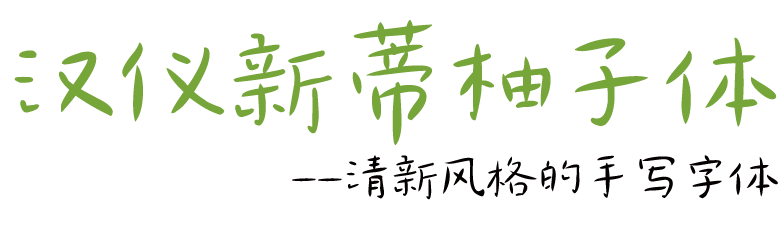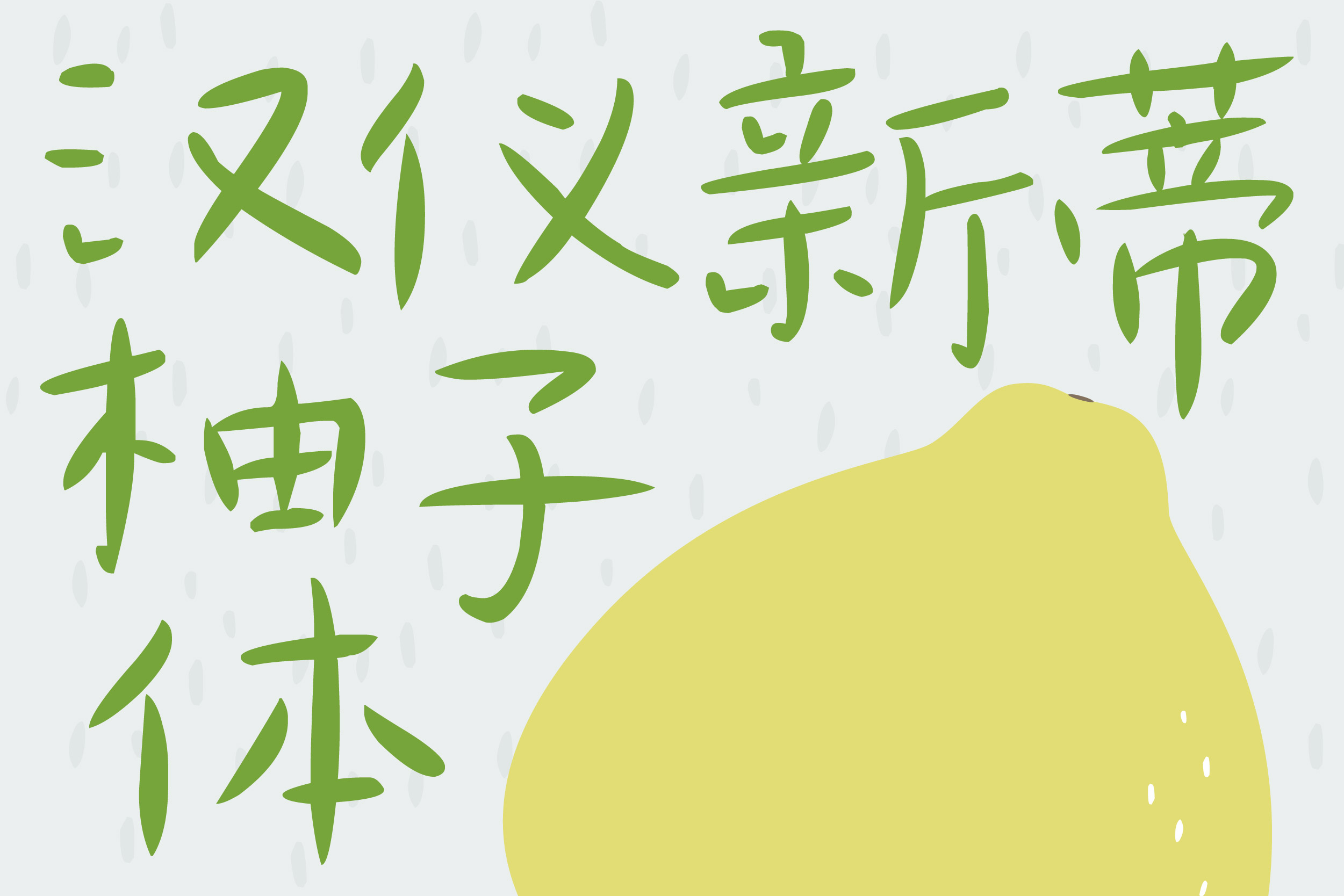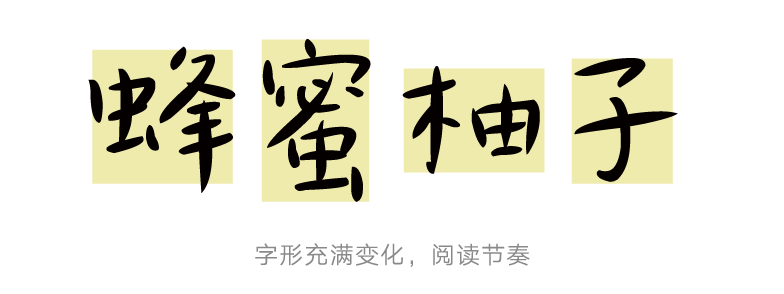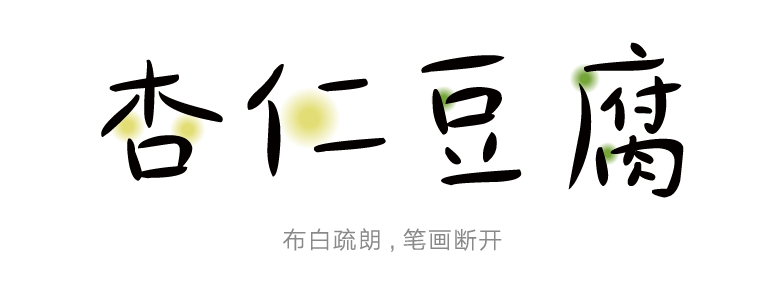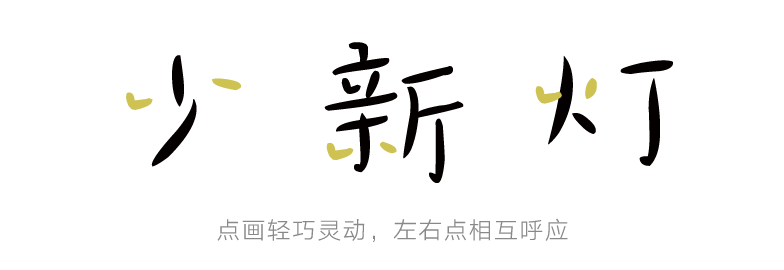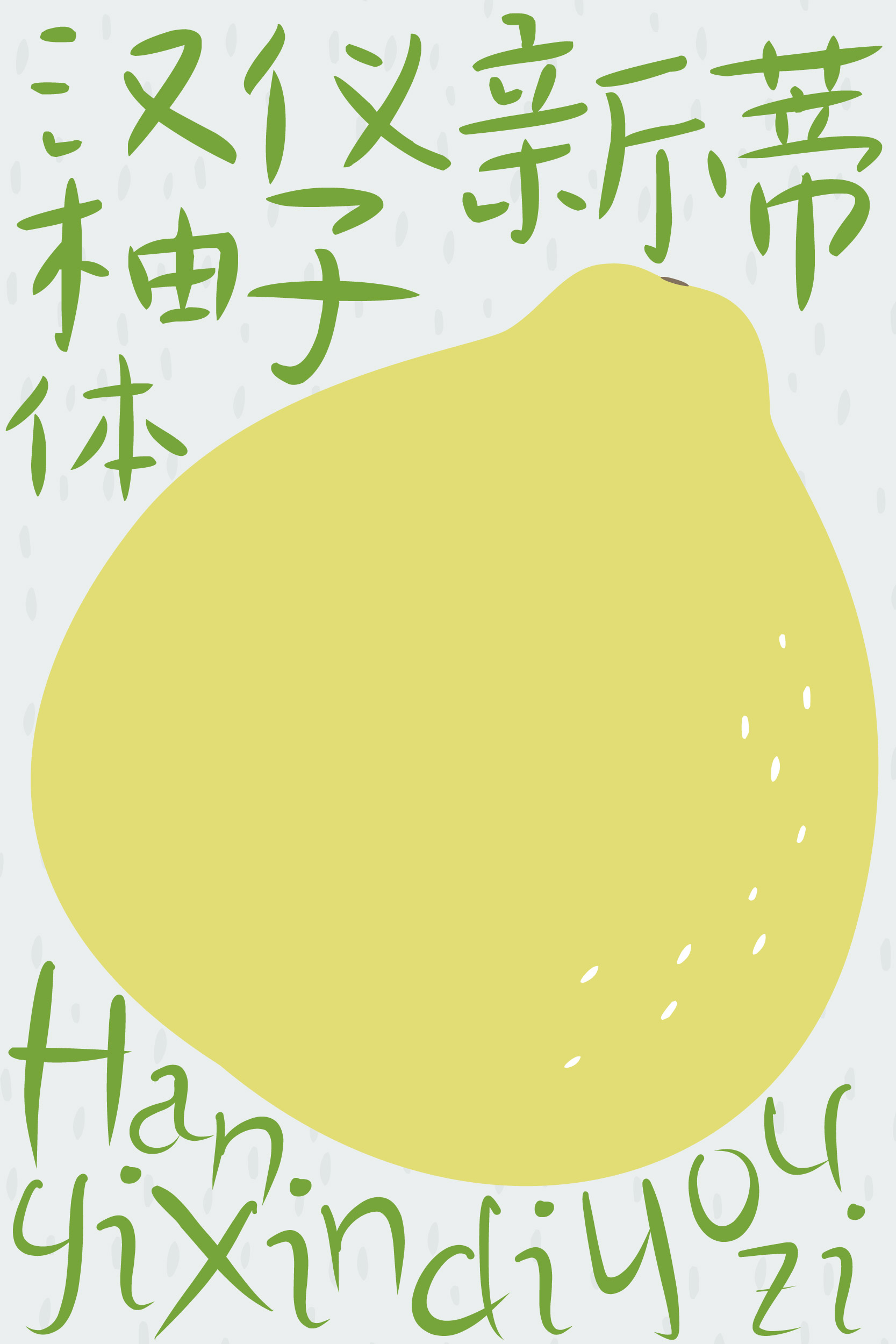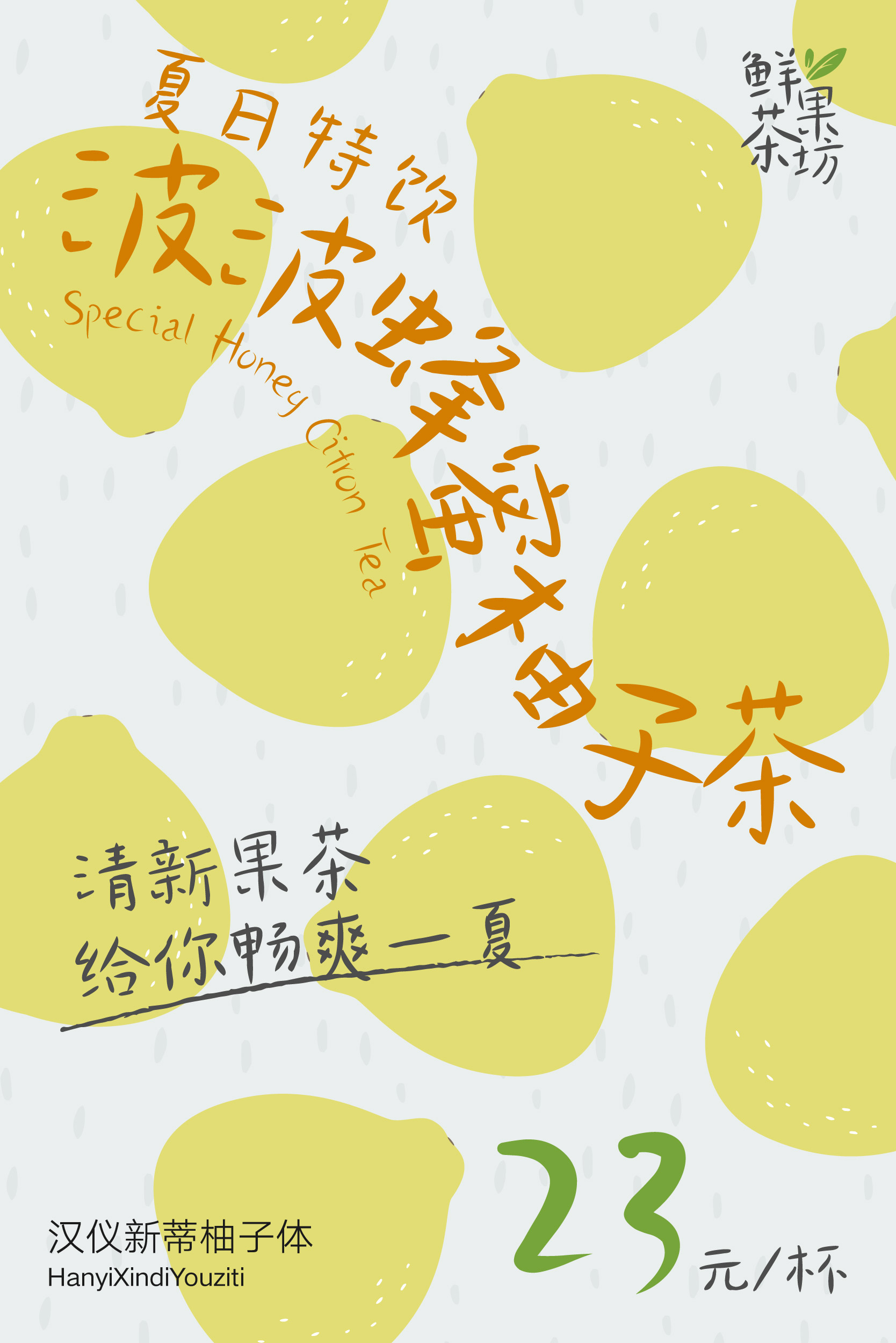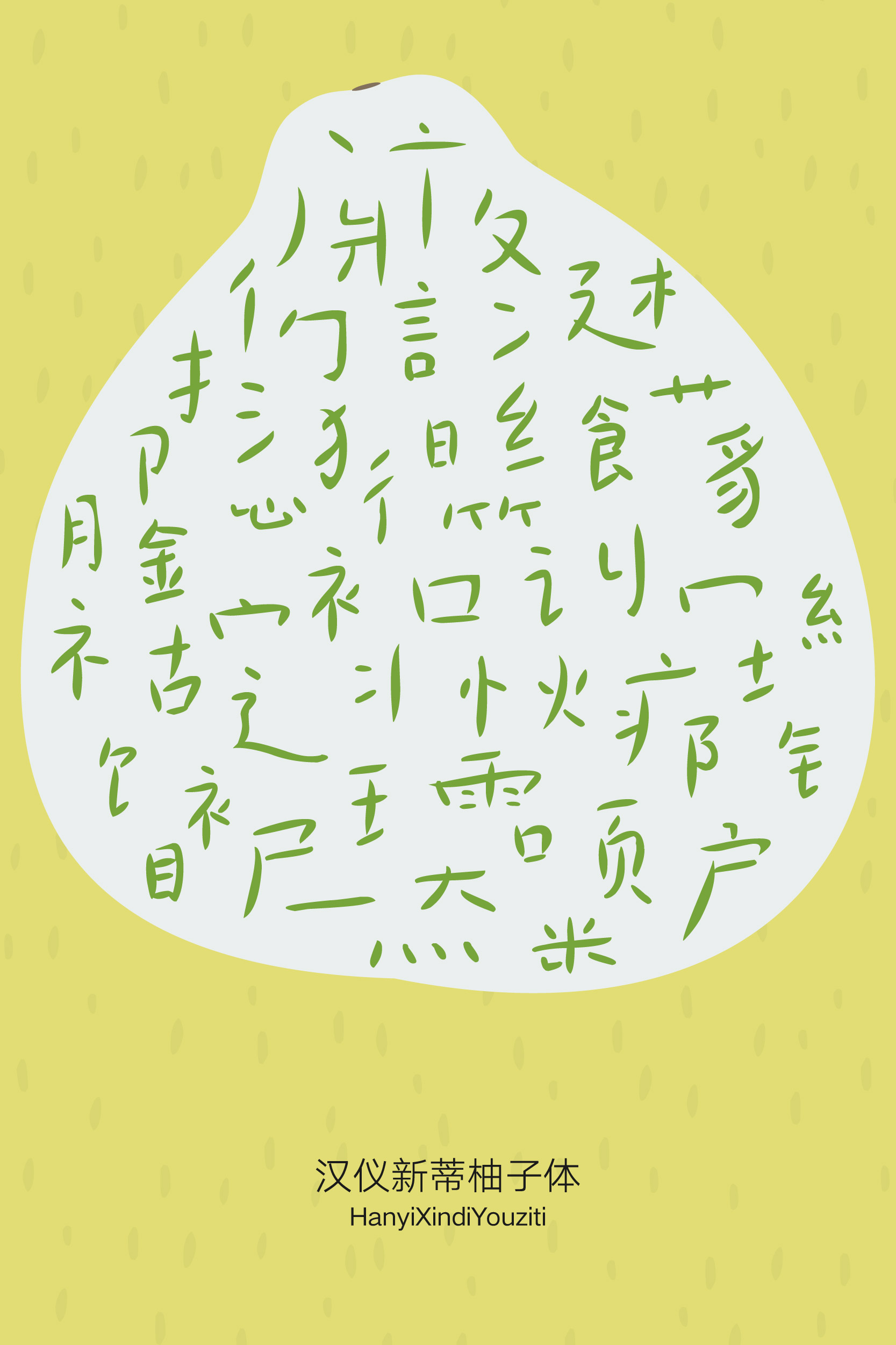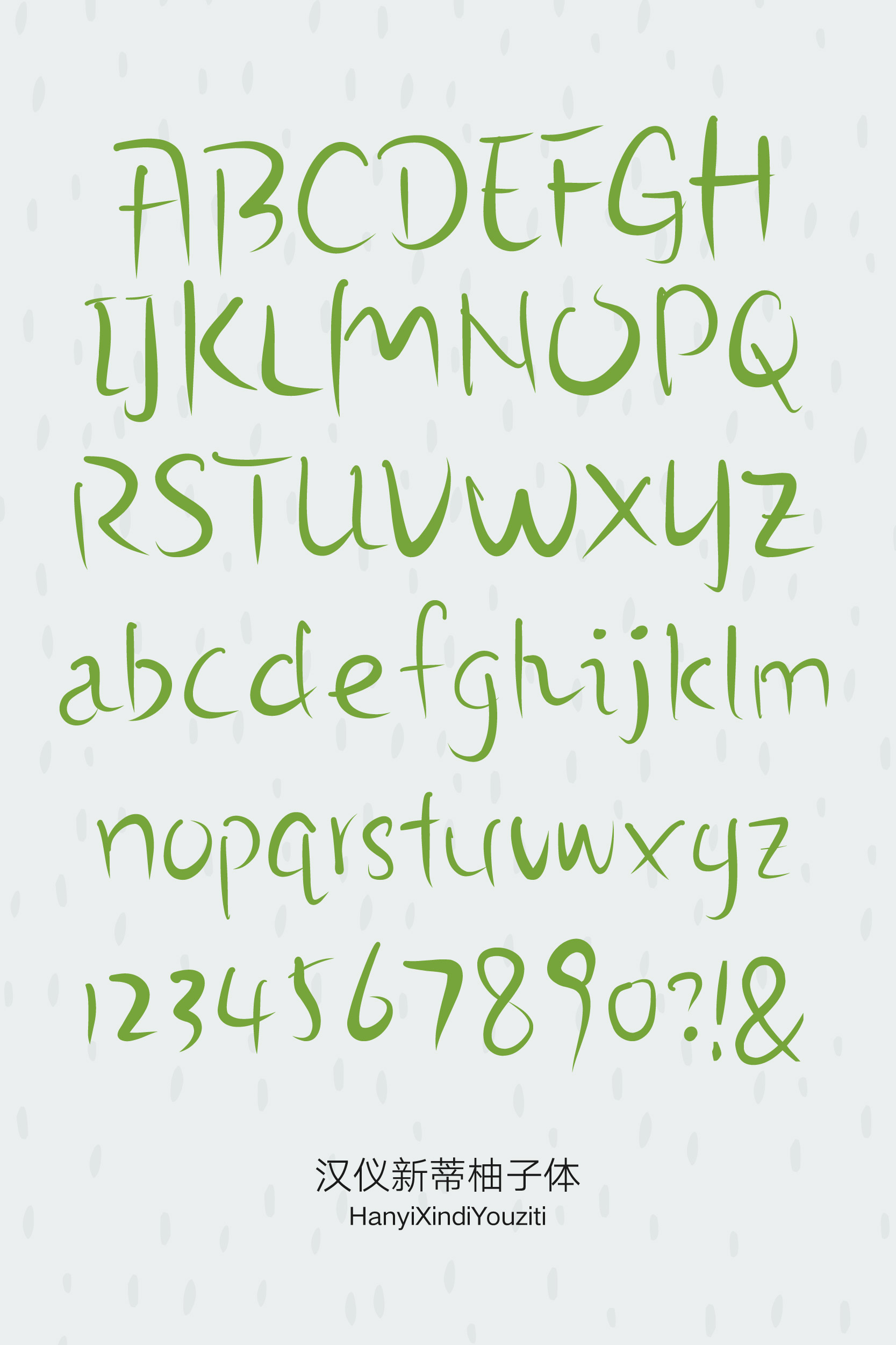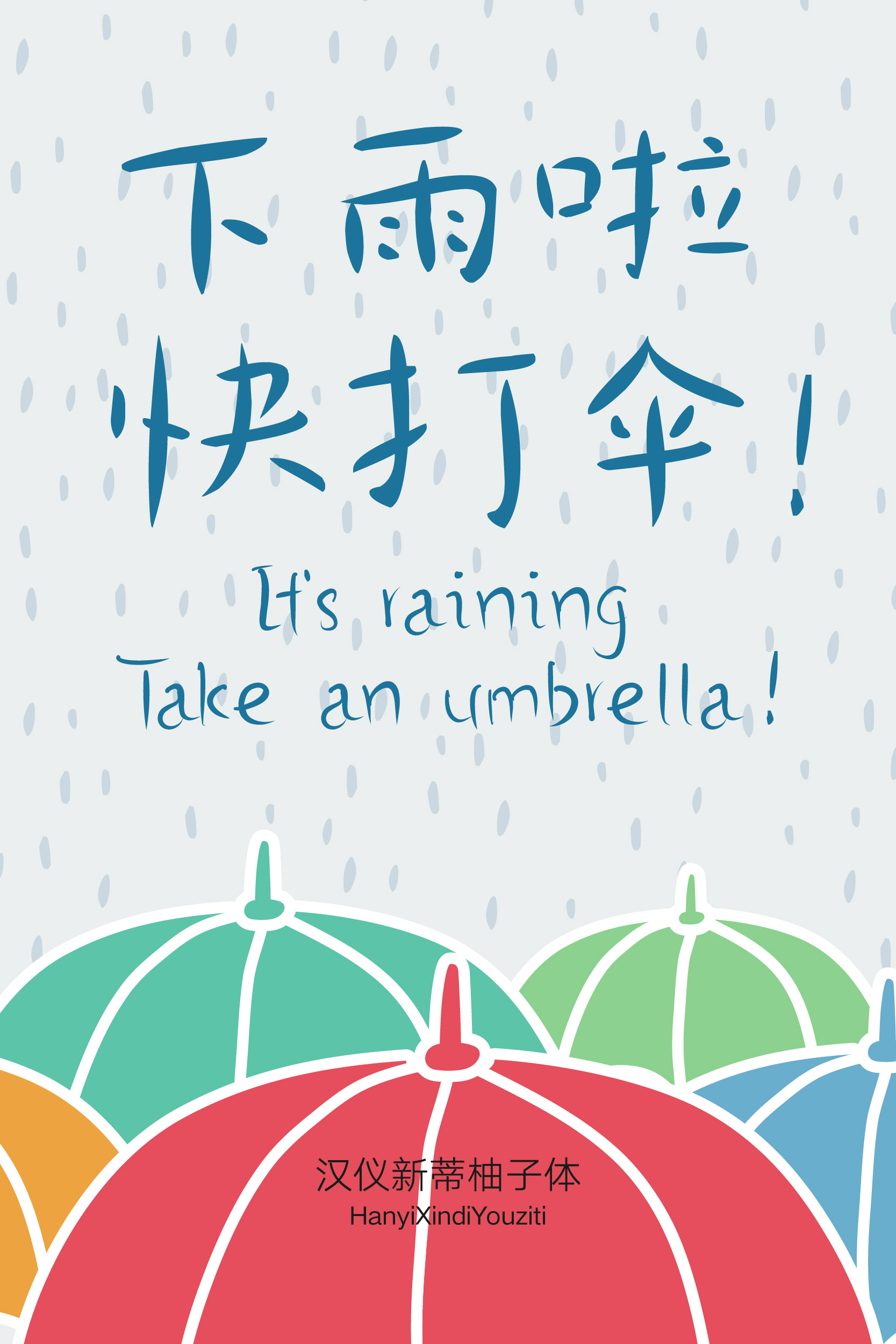
汉仪新蒂柚子体字体介绍,一款清新自然的手写字体
清新 / 自然 / 轻松 / 舒适
汉仪新蒂柚子体是一款清新自然的手写字体。字形大小错落,富有节奏感;空间疏朗透气,笔画随性而又有趣,使人感到好像嗅到了柚子所散发出的清香一般。这款字体适合用在餐饮、包装、海报、绘本等短文案场合。
汉仪新蒂柚子体的字形充满变化,大小、高低、宽窄对比强烈,增强了阅读时的节奏感,也带来了手写的亲切感。
这款字的结构均衡,布白疏朗透气,风格轻松惬意。部分笔画之间采用了断开的处理方式,加强了这款字体的“空气感”。
汉仪新蒂柚子体的笔画随性而富有变化, 具有强烈的手写感,看上去妙趣横生。
设计师所书写的点画轻巧灵动,运笔随性自然,左右两点相互呼应,增加了书写感。